Namen eintippen, Stil wählen, PNG herunterladen. Das ist alles, und es dauert etwa zehn Sekunden.
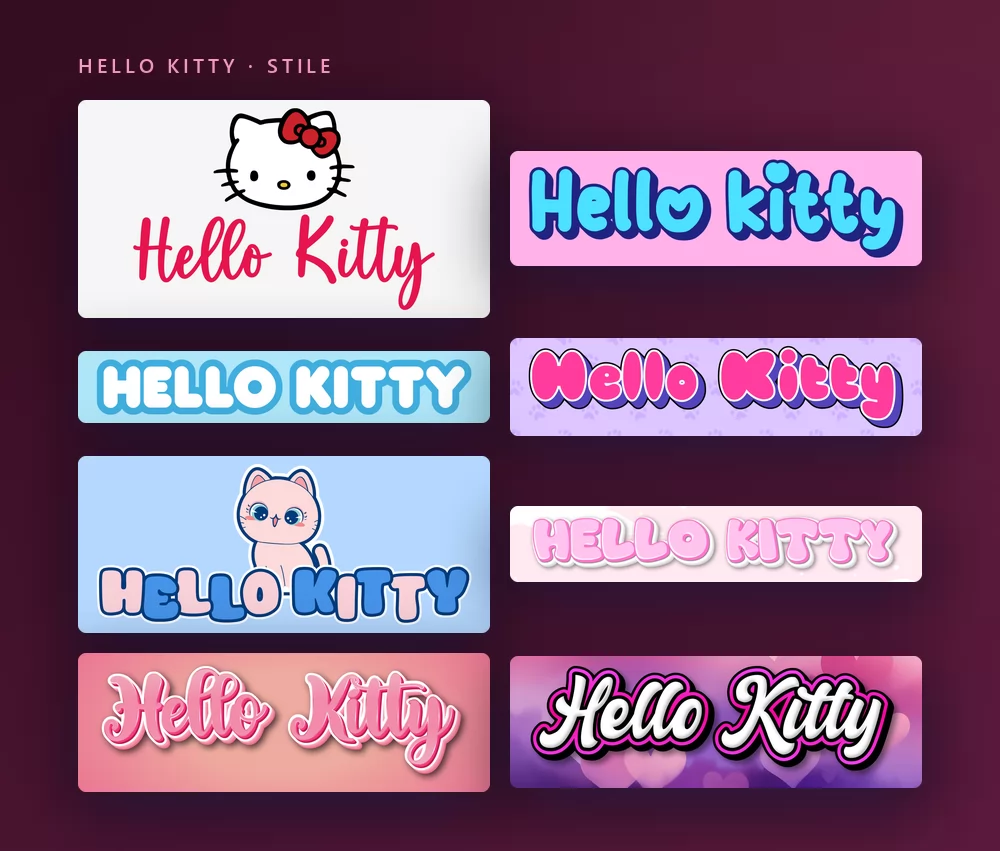
Alle stammen aus demselben Hello-Kitty-Schriftgenerator, nur mit einem anderen Stil aus der Liste. Nichts zu installieren, kein Konto.
Über die Hello-Kitty-Schrift
Hello Kitty ist eine japanische Figur, 1974 für Sanrio von der Designerin Yuko Shimizu geschaffen und seit 1980 von Yuko Yamaguchi gezeichnet. Eine weiße Katze mit roter Schleife am linken Ohr und ohne sichtbaren Mund, zuerst 1975 auf einem Vinyl-Geldbeutel zu sehen, dann eine der meistlizenzierten Figuren der Welt, auf Spielzeug, Schreibwaren, Kleidung und so ziemlich allem anderen.
Das Logo hat über die Jahre mehrere Schriftzüge gehabt, und keiner davon erschien je als Schrift: Es sind eigens gezeichnete Schriftzüge, für Sanrio entworfen. Deshalb meint „die Hello-Kitty-Schrift" für jeden etwas anderes, und deshalb listen die Schriftseiten lauter Ähnliche statt einer Antwort. Die Namen auf jeder Liste sind Janda Happy Day, Boldins, Odin Rounded, Jam Sessions, Hello Heartache und LMS Hello Kitty Hello.
Hello-Kitty-Text erstellen
Schritt 1. Den Namen eintippen
Öffne den Generator und ersetze den Beispieltext durch deinen eigenen: den Namen eines Kindes, „Alles Gute zum Geburtstag", ein Wort für einen Handy-Hintergrund. Die Buchstaben werden beim Tippen neu gezeichnet, unter Kittys Gesicht. Bleib bei Groß- und Kleinschreibung: Der Logo-Stil ist eine Schreibschrift, und ein Wort in Versalien verliert die Verbindungen, die es wie Handschrift aussehen lassen.
Schritt 2. Einen Stil wählen
Der Klassiker ist die rote Schreibschrift unter dem weißen Gesicht auf blassgrauem Hintergrund. Im Tab Stile lassen sich Füllung, Kontur und Schatten getrennt ändern, du behältst also die Buchstabenformen und nimmst die Farben woandershin: ein sanftes Rosa, ein Pastellblau für eine Cinnamoroll-Party, Weiß auf Herzen.
Schritt 3. Das Format wählen
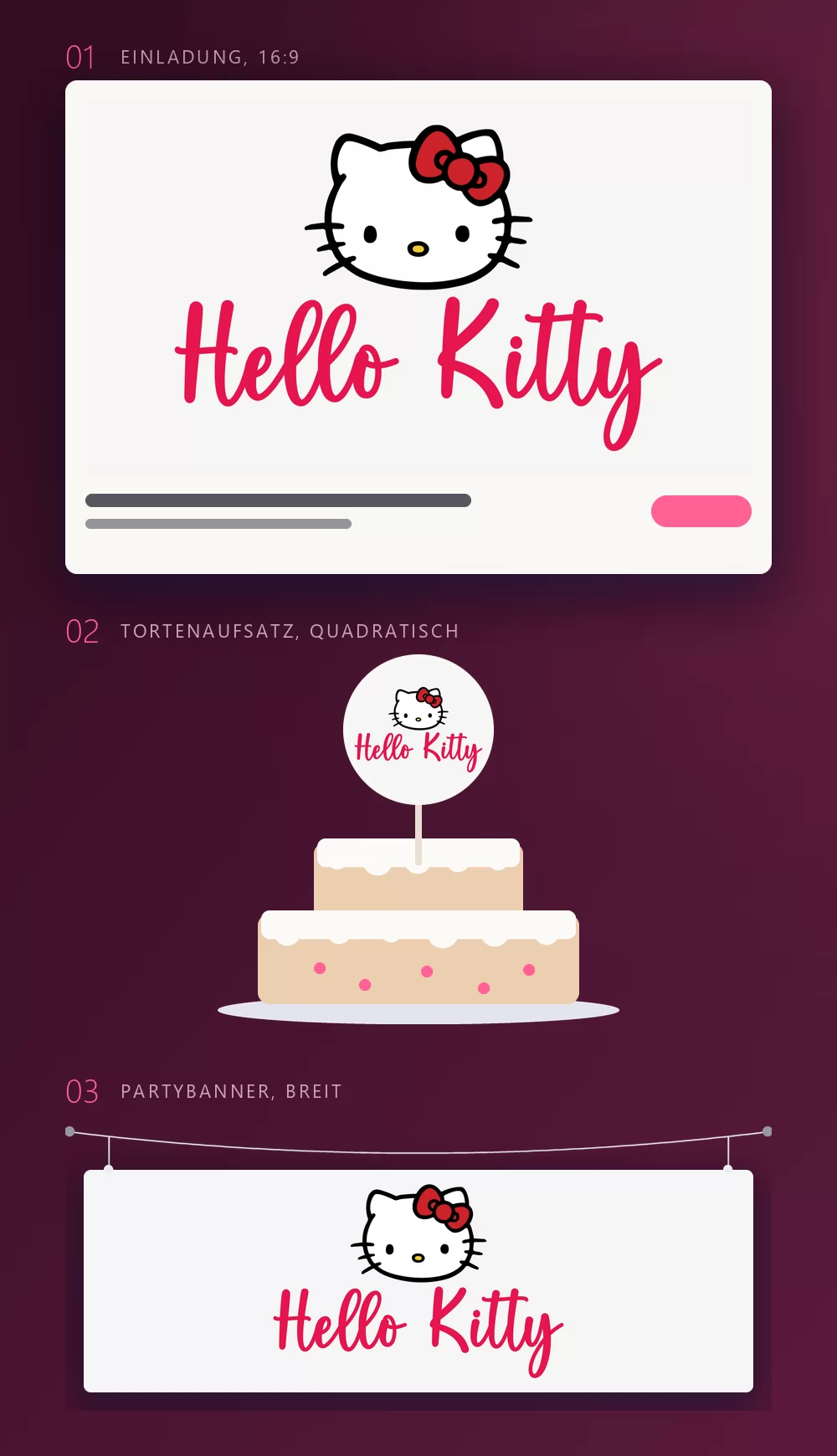
Stell das Format vor dem Export ein, dann wird später nichts beschnitten. 16:9 für eine Einladung, ein Quadrat für einen Tortenaufsatz oder Sticker, ein breiter Streifen für ein Banner quer über die Wand. Die drei Mock-ups oben zeigen, was aus diesen Formaten wird, sobald sie gedruckt sind.
Schritt 4. Herunterladen
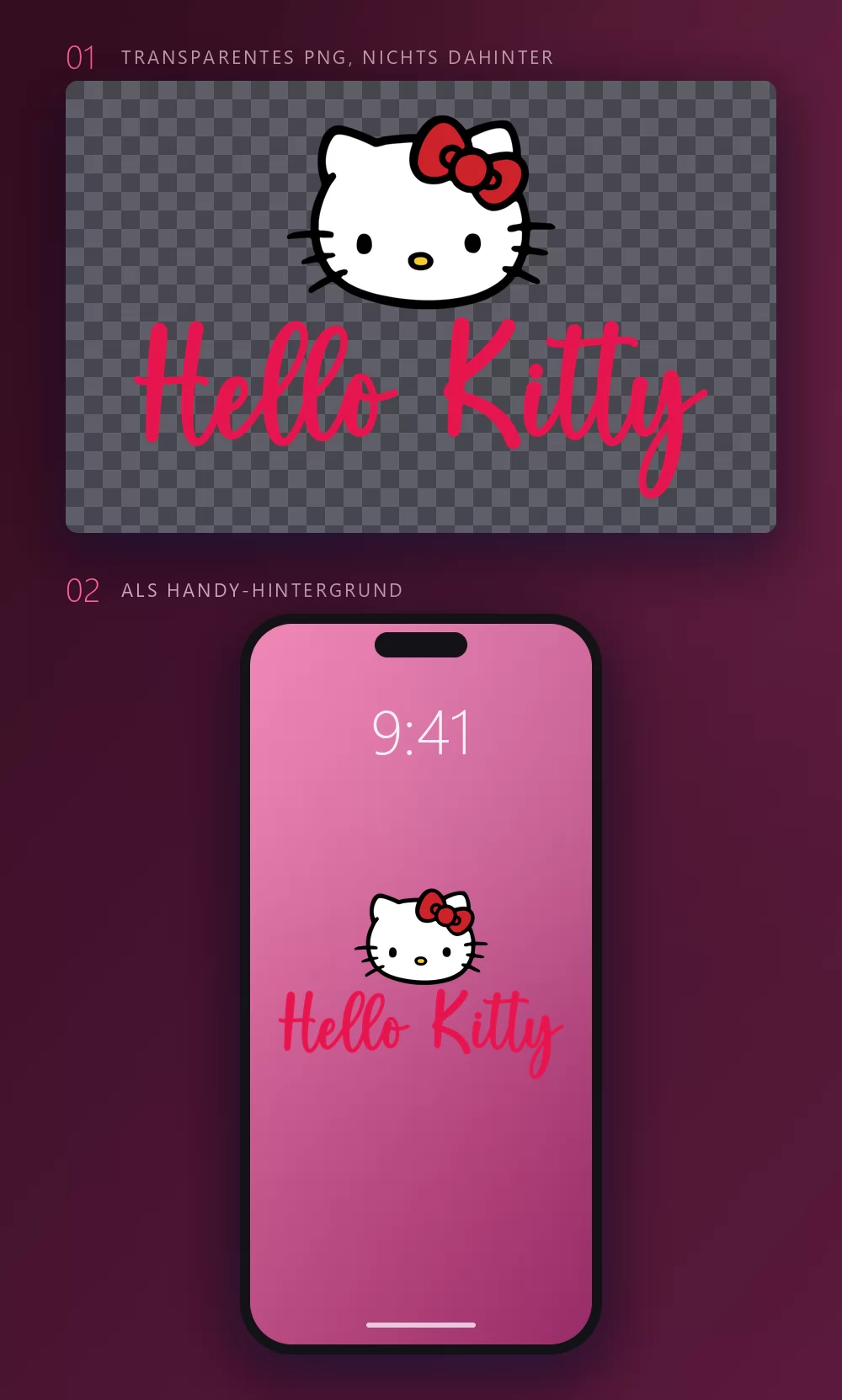
Nimm im Tab Download das transparente PNG, wenn du den Namen auf dein eigenes Design setzen willst. Diese Option übersehen die meisten, und für einen Hintergrund, einen Sticker oder eine Druckvorlage ist sie die entscheidende: dein eigener Hintergrund, Kitty und der Name darüber, kein grauer Kasten drum herum.
Lange Namen füllen die Breite schnell
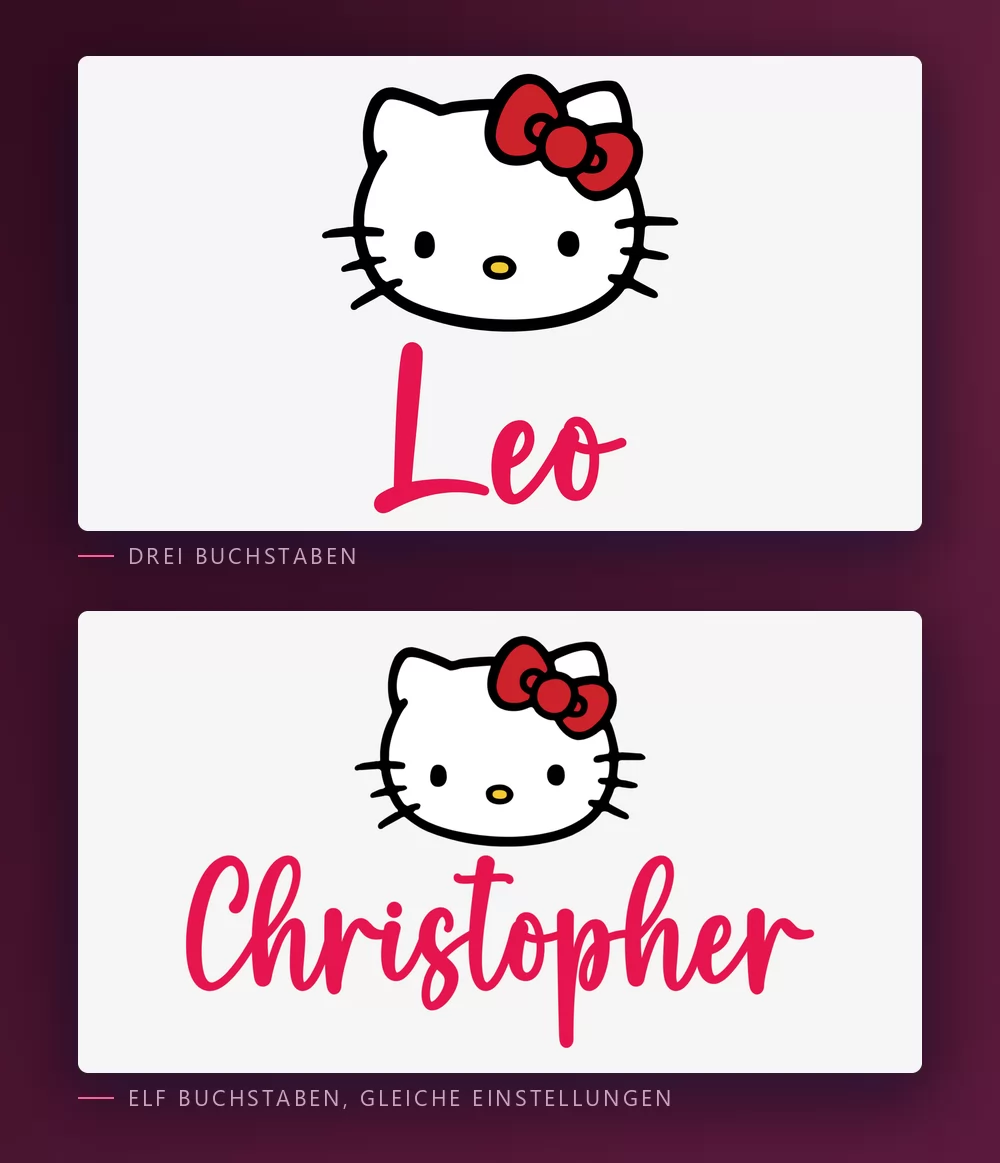
Je mehr Buchstaben, desto enger sitzen sie. Der Zeichenabstand ist ein Regler im Tab Text: etwas öffnen, und ein langer Name wirkt nicht mehr gequetscht. Derselbe Tab enthält Zoom, Zeilenhöhe, Bogen und Drehung.
Der Hello-Kitty-Look oder der Kawaii-Look
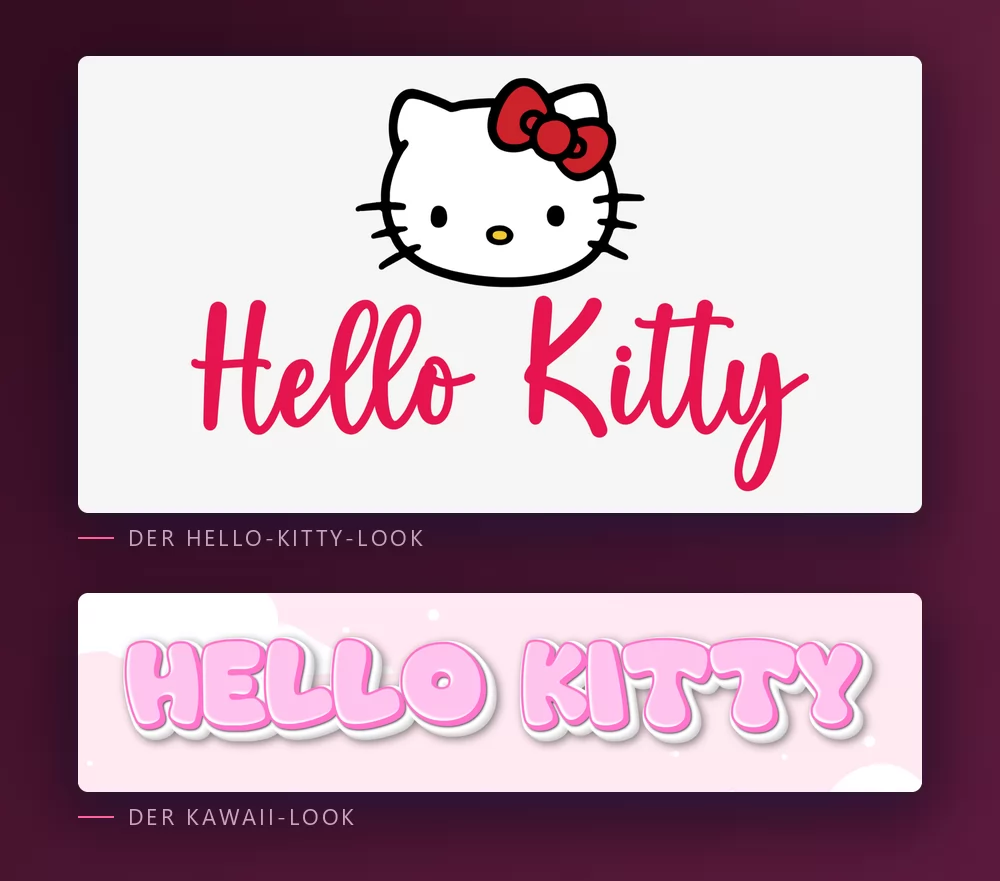
Der Hello-Kitty-Look ist das Logo selbst: das weiße Gesicht mit der roten Schleife, darunter der Name in roter Schreibschrift. Das haben die meisten im Kopf, und das ist die Wahl für alles, was auf einen Blick Hello Kitty sagen soll.
Der Kawaii-Look sind rosa Blasenbuchstaben auf Pastellwolken, ganz ohne Figur. Er trägt nichts von Sanrios Branding, was ihn zur besseren Wahl für einen Planer, ein Ladenschild oder einen Handy-Hintergrund macht, der einfach nur niedlich sein soll. Der Kawaii-Textgenerator hat ihn als Voreinstellung.
Welche Schrift, wenn du eine installieren willst
Das Logo selbst ist keine Schrift. Es ist ein für Sanrio gezeichneter Schriftzug, also ist jede Datei namens „Hello-Kitty-Schrift" jemandes Nachbildung davon oder eine Schrift, die zufällig ähnlich aussieht.
Janda Happy Day von Kimberly Geswein steht auf den meisten Listen ganz oben: eine hüpfende, runde Handschrift, die sich wie das Logo liest. Auf DaFont ist sie als kostenlos für den privaten Gebrauch gelistet, mit über achthunderttausend Downloads.
Odin Rounded ist die kostenlose mit sauberer Lizenz: eine schlichte runde Grotesk, auf DaFont als 100 % kostenlos gelistet, über eine halbe Million Downloads. Sie gibt dir das weiche, runde Gefühl der Wortmarke ohne das Hüpfen.
Boldins ist eine weitere Schreibschrift für den privaten Gebrauch, die genannt wird, und LMS Hello Kitty Hello, seit 2001 auf FontSpace mit über einer Million Downloads, ist Freeware nur für nichtkommerzielle Nutzung. Lies die Readme, bevor eine davon auf etwas kommt, das du verkaufst.
Für Kundenarbeit, wo die Lizenz sauber sein muss, sind die ehrlichen Optionen die runden Schriften mit offener Lizenz auf Google Fonts: Comfortaa, eine geometrische Rundschrift, die der Wortmarke am nächsten kommt, und Fredoka, hüpfender, mit einer ganzen Reihe von Schnitten. Keine davon ist eine Hello-Kitty-Schrift. Beide geben dir den weichen runden Look mit einer Lizenz, die niemand anzweifeln kann, und beide stehen in Canva bereit.
Wie bekomme ich einen transparenten Hintergrund für ein Hintergrundbild? Wähl im Tab Download das transparente PNG und setz Kitty und den Namen dann auf dein eigenes Foto oder deinen Verlauf.
Warum sieht mein Text neben dem echten Logo falsch aus? Meist wegen des fehlenden Gesichts, nicht wegen der Schrift. Die rote Schreibschrift allein ist nur eine rote Schreibschrift. Mit dem weißen Gesicht und der roten Schleife darüber liest sie sich als Hello Kitty, sogar in einer anderen Schrift.